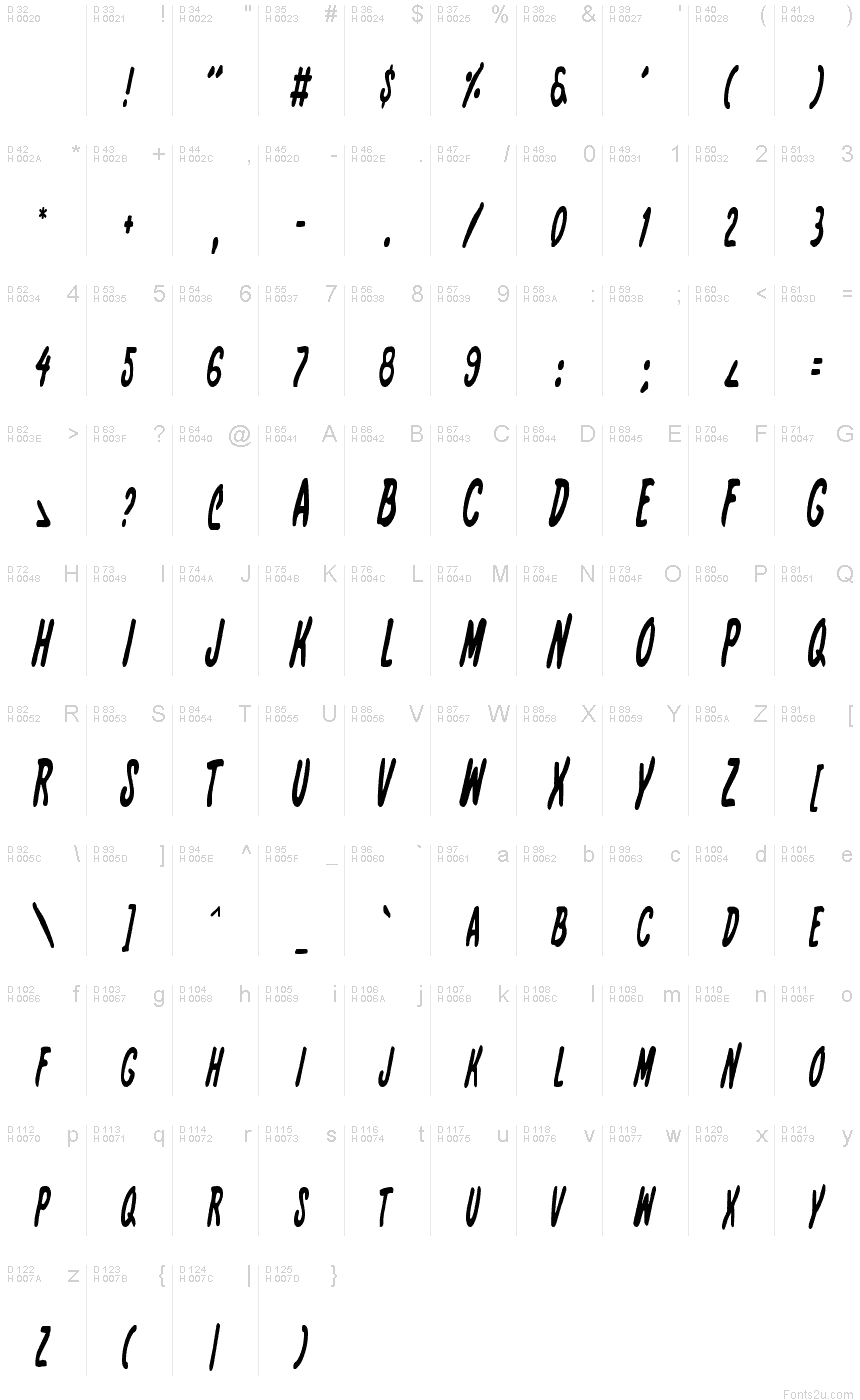
International Super Hero Cond di Iconian Fonts è un carattere tipografico gratuito in stile fumetto, con lettere alte e pennellate che sembrano schizzate sulla pagina. Le sue forme condensate racchiudono molta energia in spazi ristretti, perfette per titoli d'impatto che non soffocano il layout. Leggere inclinazioni e curve irregolari le danno quel fascino tipico dei vecchi fumetti: audace, rapida e leggermente grezza.
Con International Super Hero Cond, i tuoi titoli trasmettono subito un senso di azione. È ideale per copertine di fumetti, inviti a feste a tema supereroi, poster per bambini, loghi di giochi, miniature di YouTube e sticker giocosi. Questo font gratuito dà il meglio di sé in grandi dimensioni, lasciando che i tratti inchiostrati e le forme strette si esprimano al meglio. Abbinalo a un sans serif geometrico pulito per il testo principale, così da mantenere un aspetto accattivante ma non caotico.